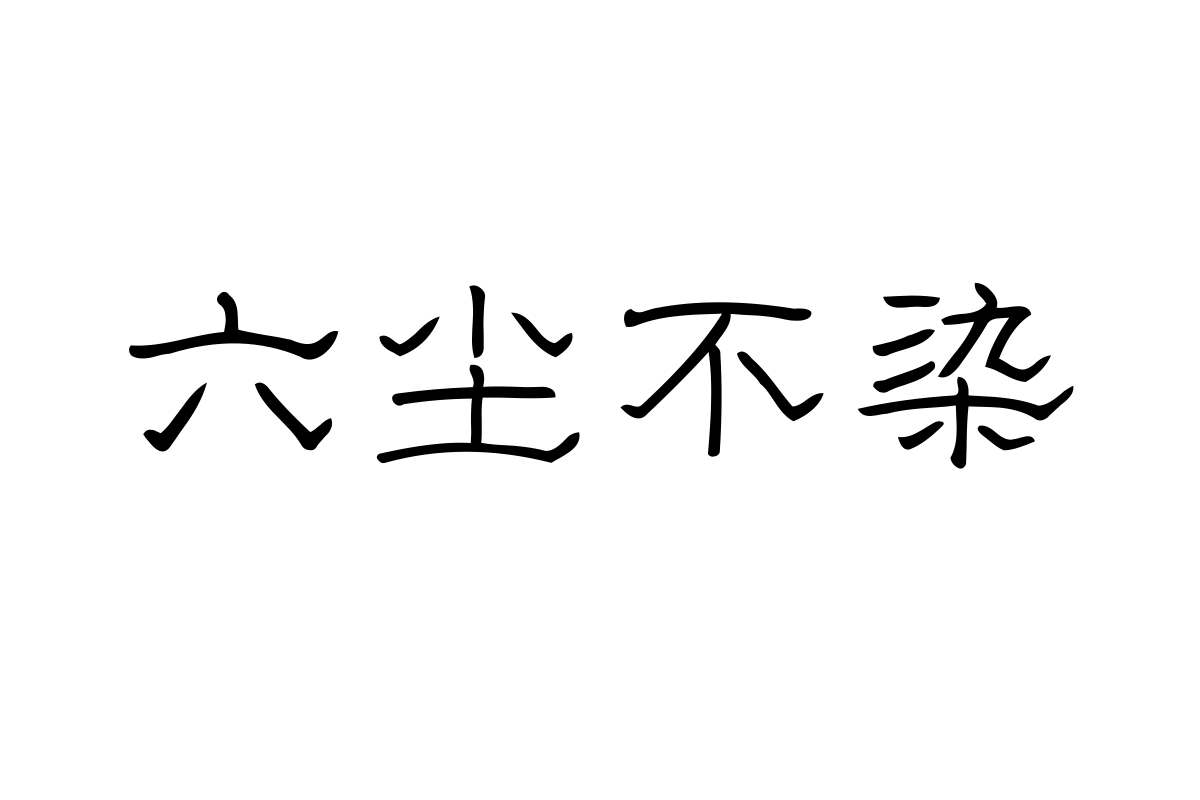
蝉羽爱如和风是一款具有现代感的中文字体,由北京华文字库有限公司设计。这款字体以其独特的设计和优雅的线条而受到广泛欢迎。
蝉羽爱如和风采用了简洁的笔画和流畅的线条,使得整个字体看起来非常轻盈和自然。它的笔画粗细适中,既有力量感又有柔美感,给人一种舒适和愉悦的感觉。
此外,这款字体还具有很好的可读性,适用于各种类型的文本和设计项目。无论是标题、正文还是广告宣传,蝉羽爱如和风都能展现出其独特的魅力和韵味。
总的来说,蝉羽爱如和风是一款非常优秀的中文字体,适合用于需要强调优雅、简洁和现代感的设计项目中。